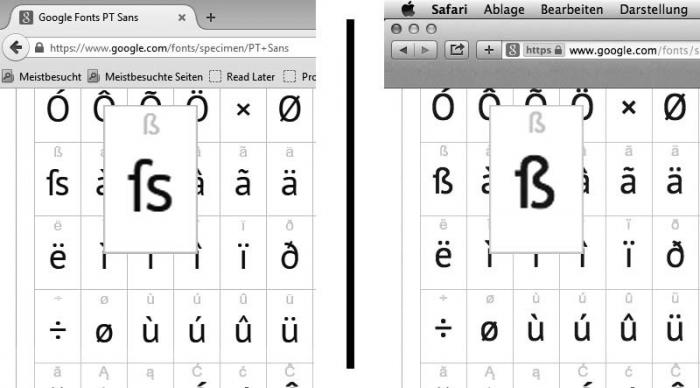
PT Sans: unterschiedliche Glyphe auf Win/Mac
ich suche nach Rat und Hilfe bei dieser Angelegenheit:
Die Glyphe des gemeinen "scharfen s" (ß) in der PT Sans macht mir etwas Sorge, da die Glyphe bei Ansicht auf einem Rechner mit OS X als Betriebssystem gänzlich anders erscheint, als bei Ansicht auf einem Windows-Rechner.
Frage: Wie kann das sein?
Auf OS X Basis zeigt mir InDesign das gemeine "scharfe s" als scharfes s so an: "ß"
Der Glyphenpalette entnehme ich: GID: 161, Unicode: 00DF, Name: LATIN SMALL LETTER SHARP S
Auf Windows Basis zeigt mir InDesign das gemeine "scharfe s" als historische Ligatur: langes s und s
(Bedaure, ich weiß nicht, wie ich die angesprochene Ligatur hier nun darstellen lassen kann!)
Der Glyphenpalette entnehme ich (auch auf Windows-Basis): GID: 161, Unicode: 00DF, Name: LATIN SMALL LETTER SHARP S
Können Sie sich erklären, wie die unterschiedliche Glyphe einmal da und einmal dort auftreten kann?
Also bei mir wird unter Windows 7 pro im Feuerfuchs das heute üblicher Eszett angezeigt und nicht die Version mit ſs. Dunkel meine ich mich zu erinnern, daß es mal eine frühe Version der PT Sans gab mit ebensolchen Eszett, was hier im Forum auch diskutiert wurde. Leider finde ich den Faden nicht mehr.
Ist ev. auf dem Windowsrechner diese alte Version der PT Sans installiert und der Browser nimmt möglicherweise diese statt der eingebetteten?
Das vermute ich auch. Das von Google Fonts benutzte Stylesheet versucht auch explizit, lokal installierte Schriftversionen einzubinden:
Versuch mal diese Testseite (die explizit nur den Webfont referenziert)! Wie sieht’s damit aus?
Ihre Annahmen waren gänzlich richtig!
Eine ältere Version der PT Sans lag auf dem Windows-Rechner.